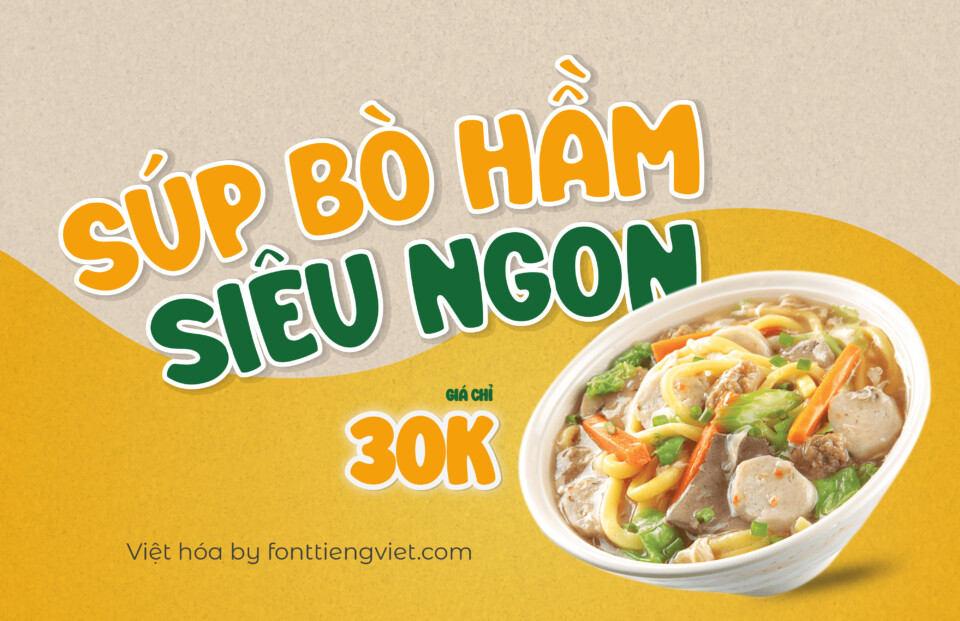
Font Việt hóa 1FTV VIP Super Boys
Giới thiệu về bộ Font Việt hóa 1FTV VIP Super Boys
Trong thế giới thiết kế đồ họa dành cho lứa tuổi học đường, việc lựa chọn một Font Miễn Phí có phong cách năng động là điều vô cùng quan trọng. Font Việt hóa 1FTV VIP Super Boys nổi lên như một lựa chọn hàng đầu nhờ thiết kế hiện đại, tinh nghịch và đầy sức sống. Đây là bộ phông chữ được tinh chỉnh kỹ lưỡng để phù hợp với bảng mã tiếng Việt, giúp các bạn học sinh và thầy cô dễ dàng tạo ra những ấn phẩm truyền thông ấn tượng mà không lo lỗi hiển thị. Với các đường nét dày dặn, bo tròn thân thiện, bộ font này mang lại cảm giác vui tươi, rất thích hợp cho các dự án báo tường, banner sự kiện hay trang trí slide bài giảng điện tử thêm phần sinh động.
Đặc điểm nổi bật của Font Việt hóa 1FTV VIP Super Boys
Thiết kế tối ưu cho giáo dục và trẻ em
Điểm mạnh của Font Việt hóa 1FTV VIP Super Boys chính là tính ứng dụng cao trong môi trường giáo dục. Các ký tự được thiết kế với độ tương phản thấp, tạo sự dễ nhìn và gần gũi. Khả năng đọc hiểu của phông chữ này rất tốt, giúp học sinh tiểu học dễ dàng theo dõi nội dung trên bảng tin hoặc các tờ rơi cổ động. Ngoài ra, bộ font còn hỗ trợ đầy đủ các dấu thanh tiếng Việt một cách chuẩn xác và thẩm mỹ.
Ứng dụng đa dạng trong sáng tạo nội dung
Không chỉ dừng lại ở sách vở, bạn có thể sử dụng bộ font này để thiết kế áo lớp, logo câu lạc bộ hoặc các video hoạt hình ngắn. Sự linh hoạt của nó giúp người dùng tự do sáng tạo mà vẫn giữ được nét chuyên nghiệp và đồng bộ trong phong cách đồ họa trẻ trung.